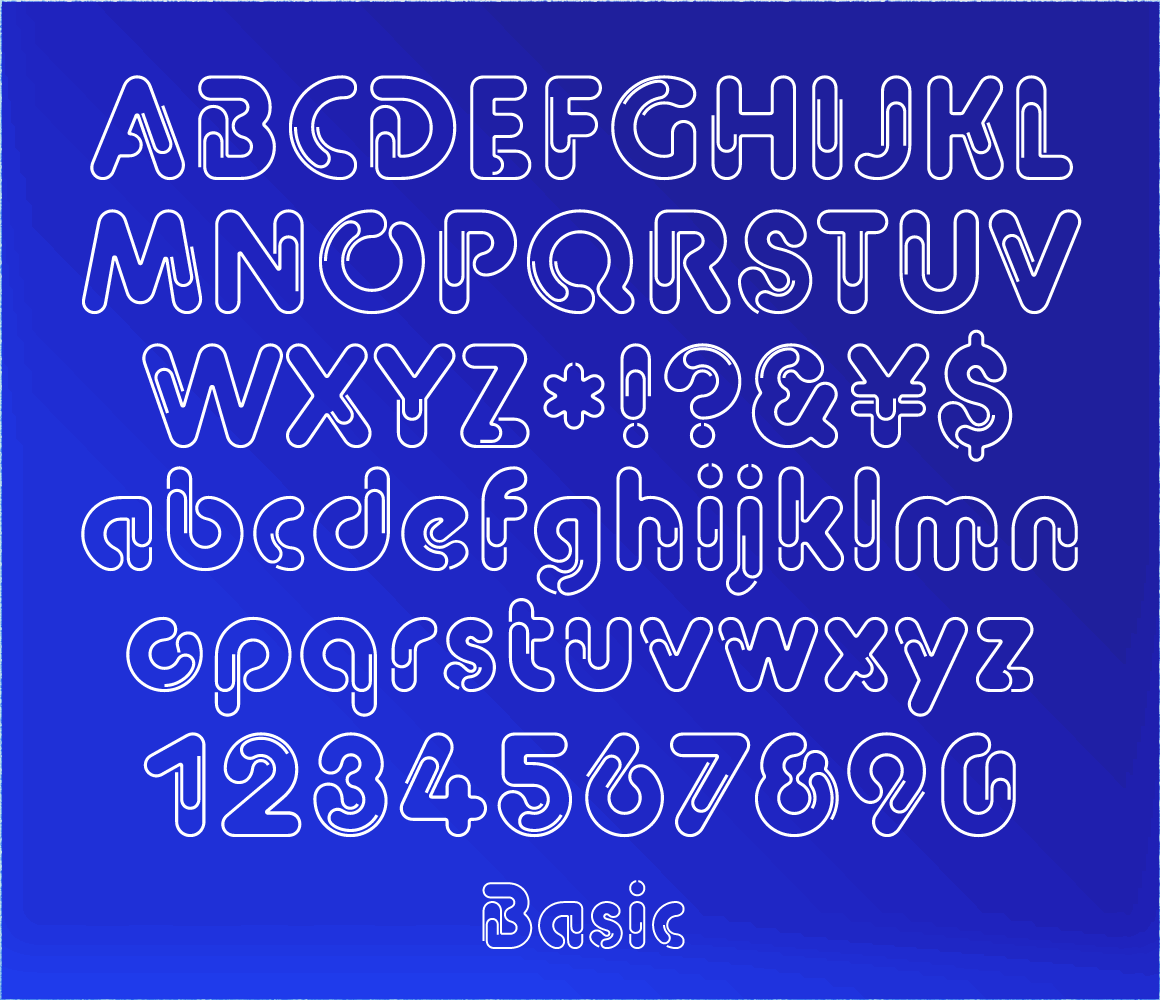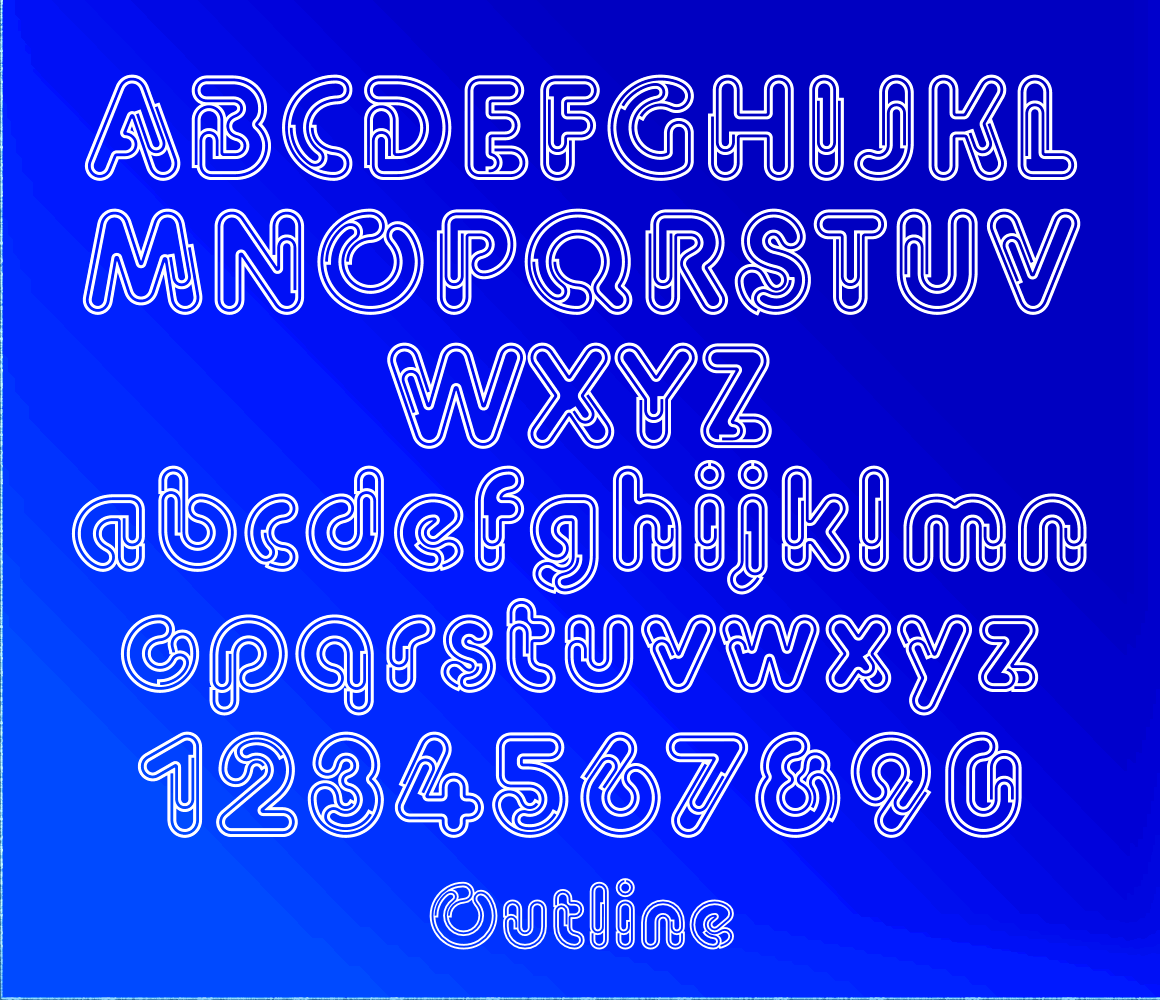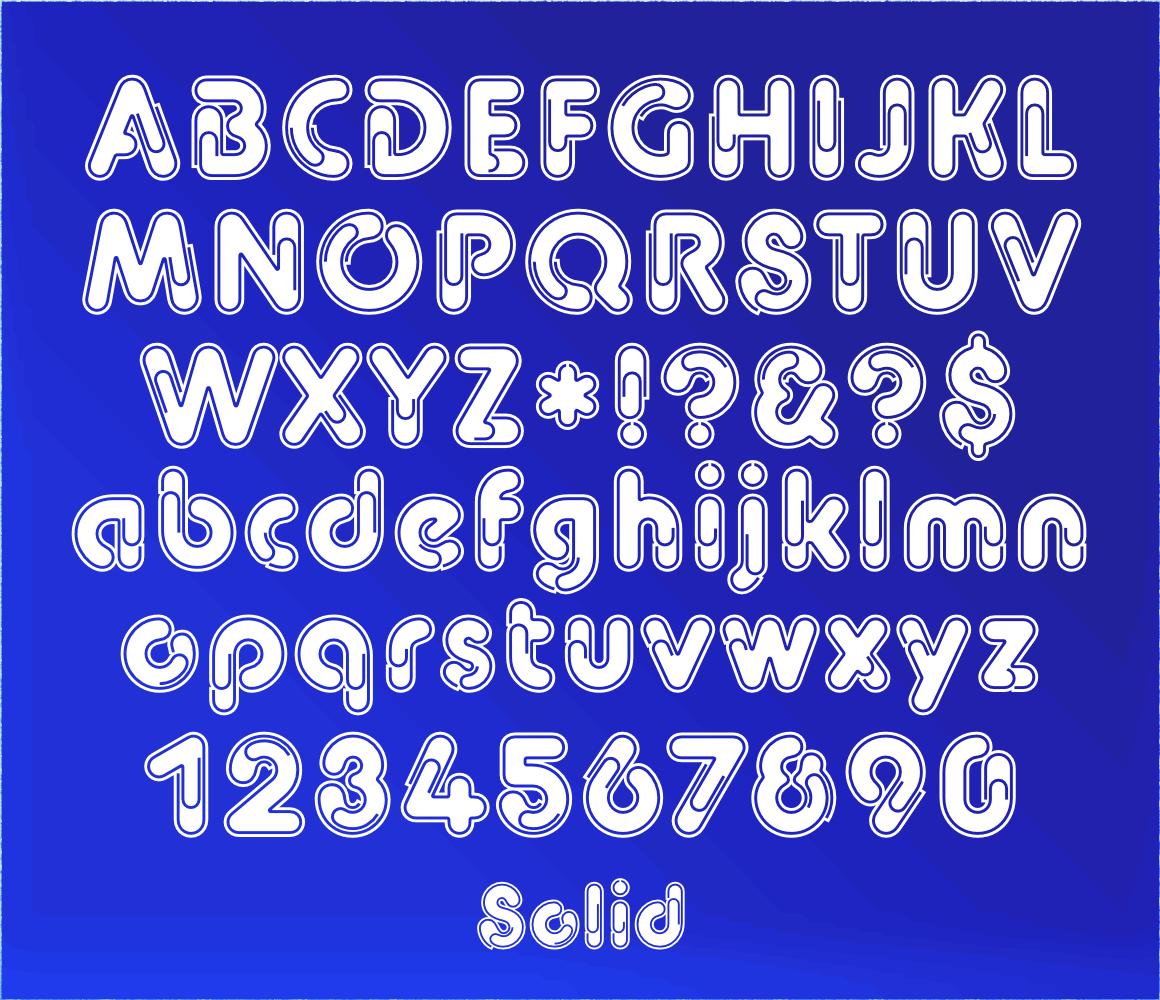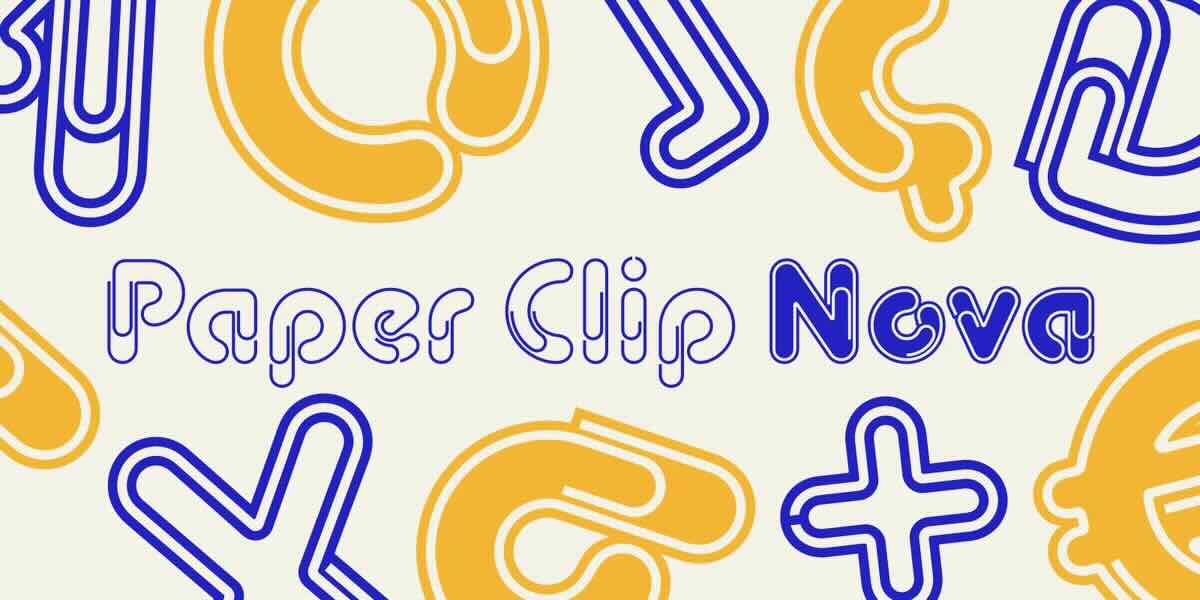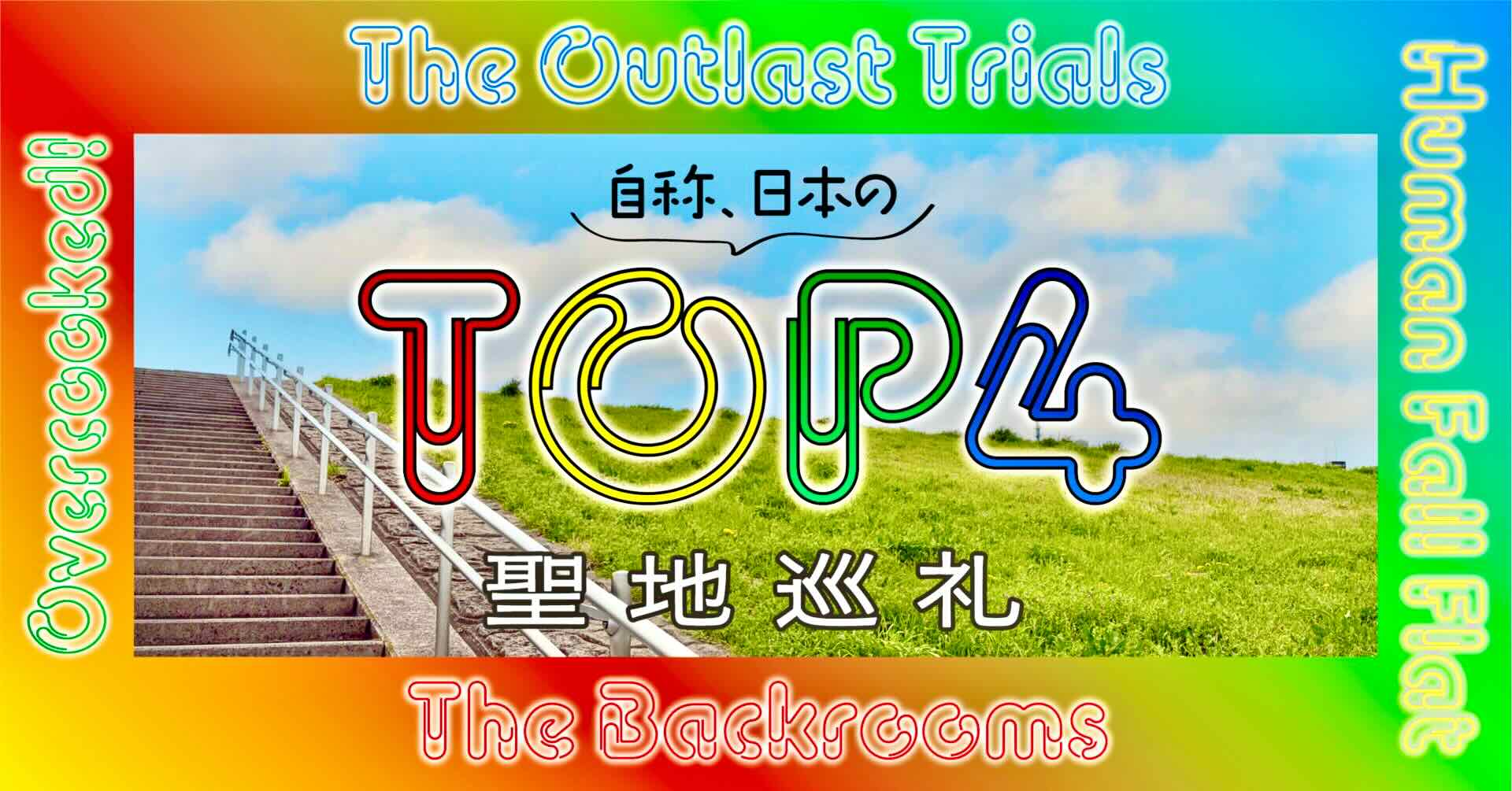
ゼムクリップをモチーフにデザインした 欧文フォント「Paper Clip」
1982年に発表したものを「Paper Clip Nova」という名に変え
リニューアルしデジタルフォント化しました
「TOP4」とは、4人のゲーム実況者グループのことらしい。
これが、Paper Clip Nova Basicです。
これは、Paper Clip Nova Outline。
そしてこれが、Paper Clip Nova Solid。
もとになった書体は、私がデザインして1982年にアメリカの会社VGCから発売された「Paper Clip」。
タイトル専用の欧文写植機用の文字フィルム商品でした。
発売時のリーフレット。
そのときは、大文字と数字がメインで、小文字はありませんでした。
1990年代に無断でデジタル化された同名のフォントが存在するが、それらは低品質なニセモノである。